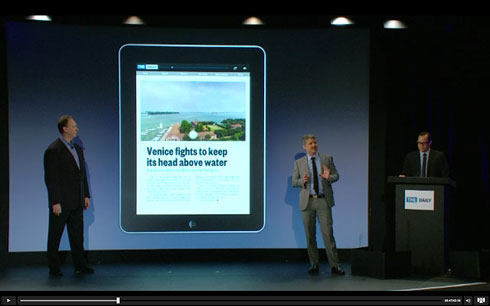
Eigentlich sollte die lang erwartete iPad-Tageszeitung »The Daily« Mitte Januar an den Start gehen. Im Dezember hofften die Apple-Jünger noch, dass Steve Jobs und der News-Corporation-Boss Rupert Murdoch ihr Vorzeigeprojekt gemeinsam vorstellen würden. Dann meldete sich zunächst der Apple-Gründer krank, anschließend musste seine Company das Abo-Modell für den Bezug von The Daily über den App-Store neu programmieren.
Der Medien-Mogul Murdoch, 1931 in Australien geboren, gilt als Vorreiter für den Wandel in der Verlagslandschaft. Er verlangte als einer der ersten von den Online-Lesern seiner Zeitungstitel Geld. Zu seiner News Corporation gehören unter anderem das Wall Street Journal sowie die Londoner Times und Sun. Murdoch kontrolliert darüber hinaus das Filmstudio 20th Century Fox, die Fox-Fernsehsender und den Bezahlsender Sky. Doch auch Murdoch macht Fehler: Im Jahr 2005 kaufte er für 580 Mio. Dollar MySpace, dessen Bedeutung nach und nach sank.
Gestern Abend war es soweit. Im New Yorker Guggenheim Museum traten die Schöpfer von The Daily vor die Presse, allen voran der 79-jährige Rupert Murdoch, scheu und steif, eingeschnürt von einer stahlblauen Krawatte. In einer 10-minütigen Ansprache dankte er zunächst Steve Jobs und Apple für des iPads und die Zusammenarbeit mit seinen Redakteuren und Designern. The Daily wird es nur als iPad-Produkt geben, nicht als gedruckte Version, nicht als Internetausgabe* und zunächst auch nicht auf anderen Geräten. Für Murdoch ist es ein weiterer Versuch, digitale Zeitungsinhalte kostenpflichtig zu machen. »Wir müssen das Nachrichtengeschäft wieder existenzfähig machen«, sagte er in New York. Das iPad zwinge die Branche dazu, »unser Handwerk neu zu erfinden.«
Eine rund 120 Köpfe zählende Daily-Redaktion bereitet Tag für Tag die Inhalte für die erste Tablet-Zeitung auf. Laut SPIEGEL hat Murdoch in die Entwicklung der Digitalzeitung rund 30 Millionen Dollar investiert. Pro Woche werde die Produktion »nur« eine halbe Million Dollar kosten, das sei ein Bruchteil der Kosten, die bei einer herkömmlichen Tageszeitung für Druck und Vertrieb anfallen. Ganz nebenbei bricht die Redaktion mit einigen Gepflogenheiten der Medienbranche, »allein schon, weil der iPad-Hersteller Apple kräftig mitmischt und einen Anteil vom Kuchen haben will.« (DER SPIEGEL)
Gestern Abend in New York: die Daily-Mannschaft stellt die erste iPad-Tageszeitung vor (das gesamte Event als Video … nach dem Klick)
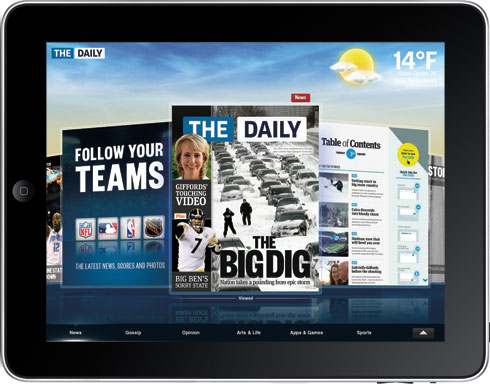
Zentraler Navigations-Dreh- und Angelpunkt bei The Daily: das Ressort-Karussell
Wie fühlt sich The Daily nun an? Die App serviert die Medieninhalte anders als WIRED (vgl. Fontblog: WIRED Screen vs. WIRED Print) und auch anders als DER SPIEGEL (vgl. Fontblog: DER SPIEGEL auf dem iPad: grafische Schlachtplatte) … was nicht schwer ist, denn die Zeitung wurde von Grund auf für das iPad konzipiert und muss kein gedrucktes Vorbild simulieren. Gleichwohl trifft man auf vertraute Gesten und Design-Eigenschaften (z. B. die 100-prozentige Aufbereitung der Seiten im Hoch- und Querformat), aber auch eine Menge neuer Ansätze.
Wie alle Printmedien baut auch The Daily auf eine Themenstruktur. Die Ressorts sind der Zielgruppe entsprechend gewählt und heißen News, Gossip, Opinion, Arts & Life, Apps & Games und Sports. Die Leser können in diese Ressorts über eine Kopf-Navigation einsteigen … oder man dreht das Karussell. Diese Metapher hat in etwa den Stellenwert eines Mac-OS-Finders oder einer Homepage, es ist das Navigationszentrum. Die Performance wie auch die Gestaltung des Karussells machen eine wackeligen Eindruck: schlecht aufgelöste Vorschaubilder, hakelige Rotation. Der Guardian schreibt: »Mit dem himmelblauen Hintergrund und der weißen Beschriftung wirkt es wie eine schlechte Microsoft-Kopie von Coverflow.« Das Karussell ist stets mit einem Fingertippen anwählbar, über ein kleines Icon in der rechten oberen Bildschirmecke.
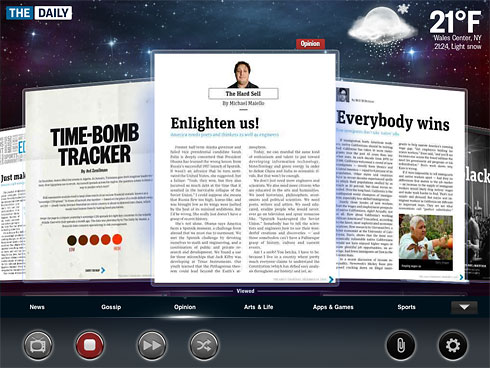
In der Karussell-Ansicht mit ausgeklappter Schalttafel wird die Zeitung zum Multimedia-Drehkreuz, mit TV- und Vorlesefunktion
Am Fuß des Karussells lässt sich ein Bedienfeld einblenden, das einen bisher nicht gekannten multimedialen Zugang zu den Inhaten einer Zeitung gestattet. Ein Vorlauf-Knopf bringt das Karussell in Schwung und lässt es so lange drehen, bis man es an einem interessanten Beitrag stoppt. Der Shuffle-Button springt nach dem Zufallsprinzip zu Artikeln, die der Benutzer noch nicht gelesen hat. Ein TV-Knopf knipst ein moderierte Video-Einführung mit den Themen des Tages an und der Kopfhörer-Schalter steht für die Vorlesefunktion – nicht für alle Beiträge aber die interessantesten. Damit bietet The Daily nicht nur Präsentationsformen, die man je nach Laune auswählen kann, sondern auch beeinträchtigten Menschen den Konsum einer Zeitung erleichtern.
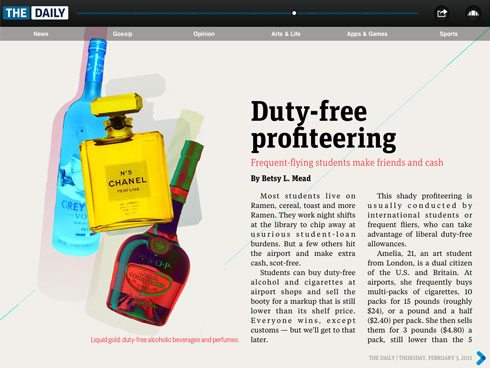
Typografische Katastrophen: Löcher im Text und gesperrte Zeilen beleidigen das Auge der Leser
Übrigens wird The Daily schon gleich nach dem Start von Werbekunden umgarnt. Beim Start der App wird das 2-wöchige Probeabo als gute Tat des US-Netzbetreibers Verizon angekündigt, und zwischen den Beiträgen gibt es bereits reichlich Werbung, überwiegend von Hollywood-Filmen und Technik-Unternehmen.
Eines ist allen digitalen Medien gemein – sofern sie sich nicht auf die pure Wiedergabe einer gedruckten Seite in PDF-Form reduzieren: die Typografie ist unter aller Sau. Zwar benutzt The Daily vorzügliche Schriften (unter anderem die FF Unit Slab von Erik Spiekermann), aber die guten Schriften auch gut zu verwenden – da scheinen Welten dazwischen zu liegen. Alleine sich vom Blocksatz zu verabschieden würde enorm helfen.
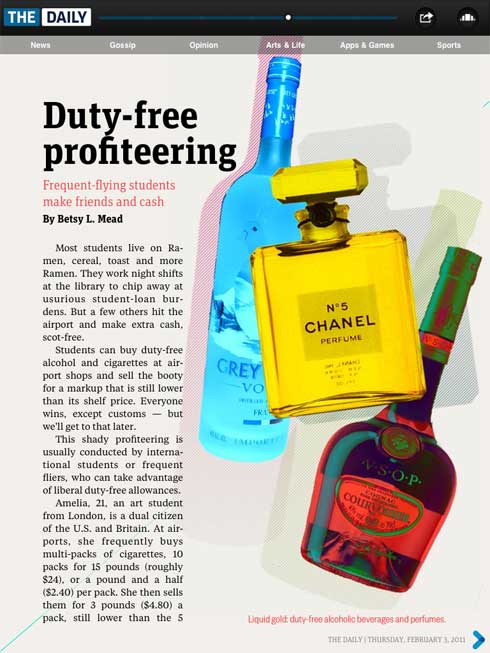
Das iPad geht in sein erstes Jahr und bis jetzt war noch niemand in der Lage ein vernünftiges Magazin/Zeitungskonzept sinvoll, benutzerfreundlich und vor allem ästhetisch für das iPad umzusetzen.
Langsam Frage ich mich wofür ich es gekauft habe.
Ausführliche Betrachtung der Typografie von The Daily bei Fonts-in-use:
Schmale Blocksatzspalten. Da würde ich ja verrückt werden.